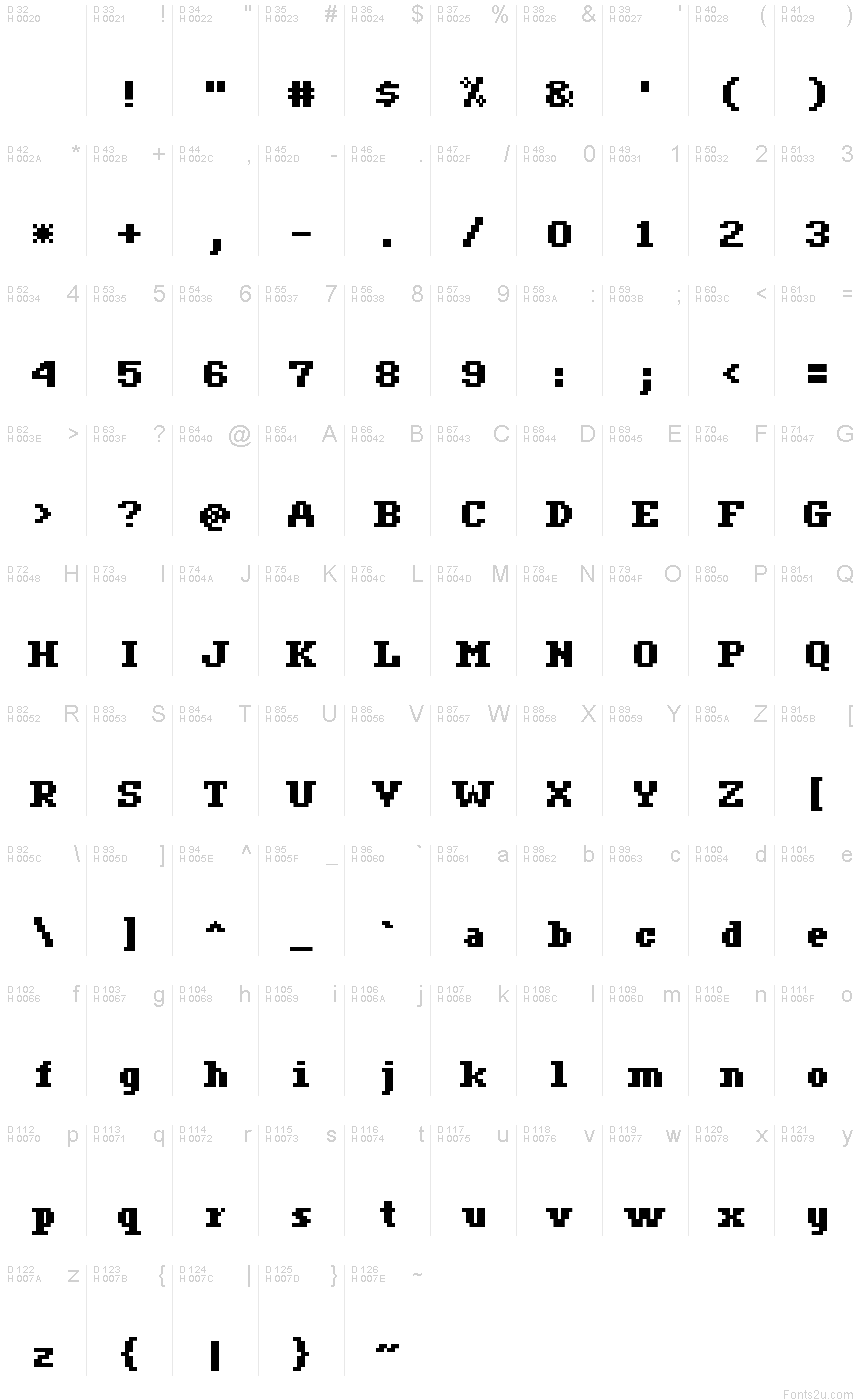
Ceriph 07_65 autorstwa Craiga Kroegera to darmowy szeryfowy font bitmapowy o surowym charakterze niskiej rozdzielczości i klimacie wczesnych cyfrowych ekranów. Litery są masywne i zwarte, mają kwadratowe narożniki, schodkowe krzywizny i subtelne szeryfy, dzięki czemu prosta siatka pikseli zyskuje typograficzny wyraz, wykraczając poza czystą użyteczność.
Sprawdzi się wszędzie tam, gdzie chcesz, aby surowa cyfrowa tekstura grała główną rolę: w menu gier, zinach, nagłówkach stron, podpisach plakatów czy oprawie muzycznej. Jako darmowy font świetnie nadaje się do krótkich tytułów, etykiet interfejsu i tekstów na okładkach, ponieważ jego klockowy rytm pozostaje wyrazisty i celowy, zamiast zlewać się w generyczny pikselowy wygląd.